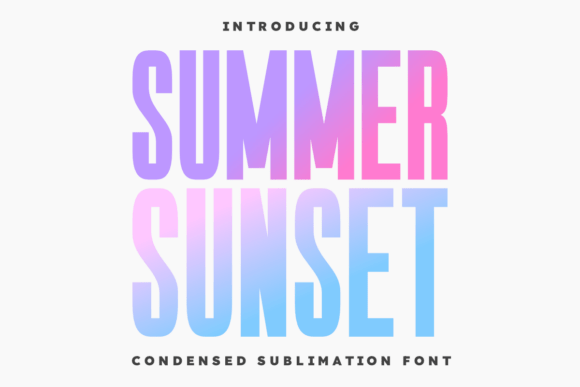
Summer Sunset
Summer Sunsetのような高品質の素材をお探しの場合、このプレミアムパッケージはクリエイティブなプロジェクトに素晴らしい選択です。
精密に作られたSummer Sunsetは、クリーンなベクター、滑らかなタイポグラフィ、そして安心のための商用ライセンスを提供します。
POD(オンデマンド印刷)製品、結婚式の招待状、またはソーシャルメディアのグラフィックを作成している場合でも、Summer Sunsetは理想的です。